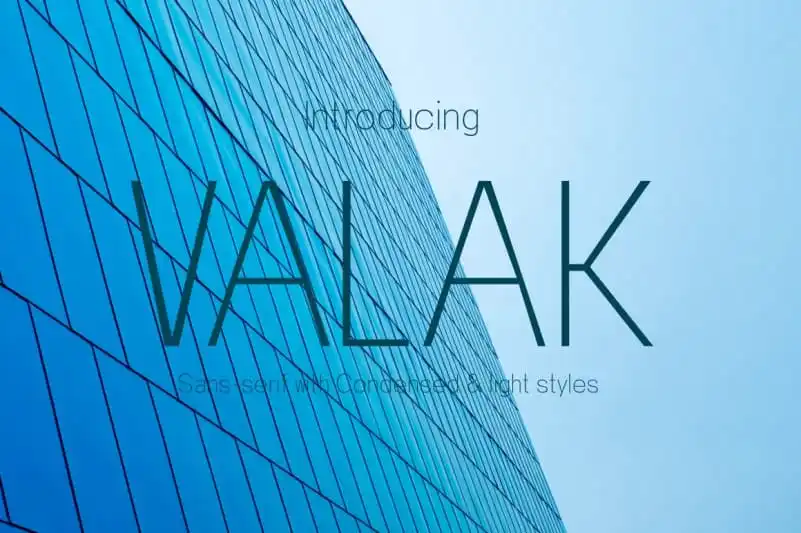
Valak Sans Serif Font – Fonte Grátis
Valak Sans Serif Font
A Valak Sans Serif é uma nova opção para designers que buscam uma fonte clean e eficiente. Manufacturada por Arief rochman, esta fonte não possui serifas, oferecendo um visual moderno e minimalista ideal para projetos de design simples ou em temáticas minimalistas. Inclui a base do alfabeto latino e do russo, sendo uma fonte que abrange caracteres básicos, incluindo letras maiúsculas e minúsculas, números e simbolos. Um ponto importante sobre esta fonte é sua única disponibilidade na opção de tamanho/estreita de luz. Ela foi projetada para oferecer flexibilidade sem comprometer a qualidade visual ou o espaço necessário em uma tela digital. Para designers que buscam um estilo contemporâneo, mas não desejam acentos adicionais, a Valak Sans Serif é perfeita. É uma escolha inteligente para criar layouts limpos e elegantes, onde os detalhes são essenciais. Seja para aplicações digitais ou impressivas, esta fonte será um recurso valioso em seu arsenal de design.